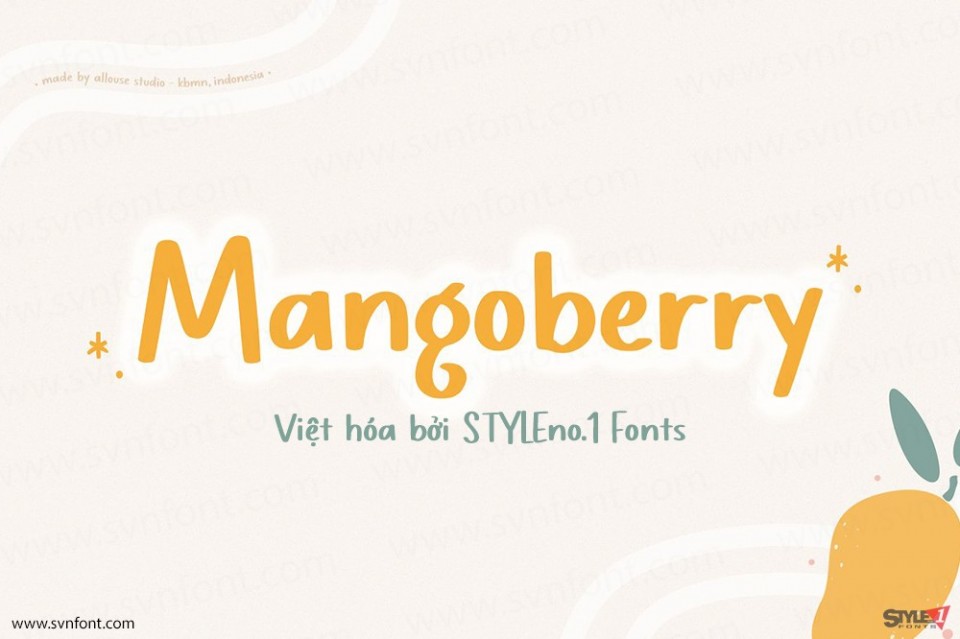
Font việt hóa SVN Mangoberry
Tải Font việt hóa SVN Mangoberry – Font Chữ Viết Tay Ngọt Ngào
Giới thiệu về Font việt hóa SVN Mangoberry
Trong thế giới thiết kế đồ họa, việc lựa chọn một Font Miễn Phí phù hợp đóng vai trò quan trọng để truyền tải cảm xúc của tác phẩm. Font việt hóa SVN Mangoberry là một bộ phông chữ viết tay mang phong cách hiện đại, trẻ trung và cực kỳ ngọt ngào. Với những đường nét thanh thoát xen lẫn chút tinh nghịch, bộ font này mô phỏng hoàn hảo nét chữ viết tay tự nhiên, mang lại cảm giác gần gũi và chân thực cho người xem. Đây là lựa chọn lý tưởng cho các bạn học sinh khi thiết kế báo tường, thiệp chúc mừng hoặc các dự án sáng tạo cá nhân tại trường học.
Đặc điểm nổi bật của Font việt hóa SVN Mangoberry
Bộ Font việt hóa SVN Mangoberry nổi bật nhờ sự linh hoạt trong các đường nét calligraphy. Các ký tự được chăm chút kỹ lưỡng về khoảng cách, giúp văn bản trở nên dễ đọc nhưng vẫn giữ được tính thẩm mỹ cao. Điểm đặc biệt nhất chính là khả năng hiển thị tiếng Việt trọn vẹn, không bị lỗi dấu, giúp các nhà thiết kế tại Việt Nam tự tin áp dụng vào mọi sản phẩm từ in ấn đến hiển thị kỹ thuật số. Font chữ này thường được dùng trong các thiết kế mang tính chất nữ tính, trang trí ảnh hay làm tiêu đề cho các video ngắn trên mạng xã hội.
Cách ứng dụng Font việt hóa SVN Mangoberry hiệu quả
Sáng tạo trong học tập và đời sống
Sử dụng Font việt hóa SVN Mangoberry giúp các slide bài thuyết trình trở nên sinh động hơn bao giờ hết. Thay vì dùng các phông chữ khô khan, sự mềm mại của Mangoberry sẽ thu hút sự chú ý của thầy cô và bạn bè. Ngoài ra, bạn có thể dùng font này để làm logo cá nhân, nhãn vở hoặc trang trí sổ tay Bullet Journal. Để đạt hiệu quả tốt nhất, hãy kết hợp font với các tông màu pastel nhẹ nhàng như hồng, xanh lá hoặc cam nhạt để tạo nên tổng thể hài hòa và bắt mắt.
Kết luận và tải Font việt hóa SVN Mangoberry